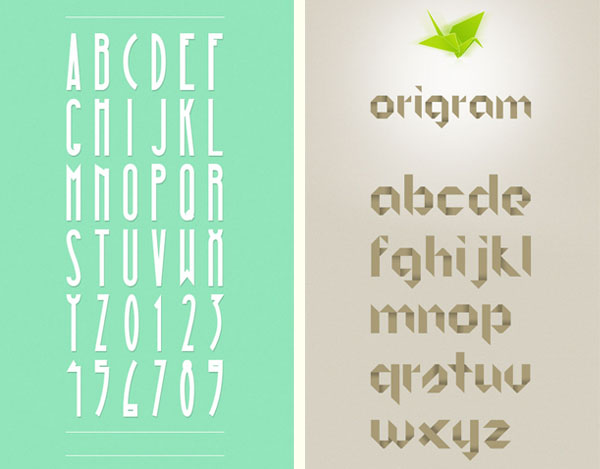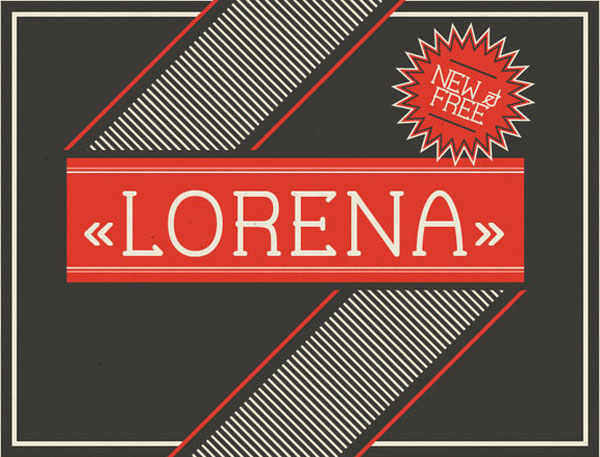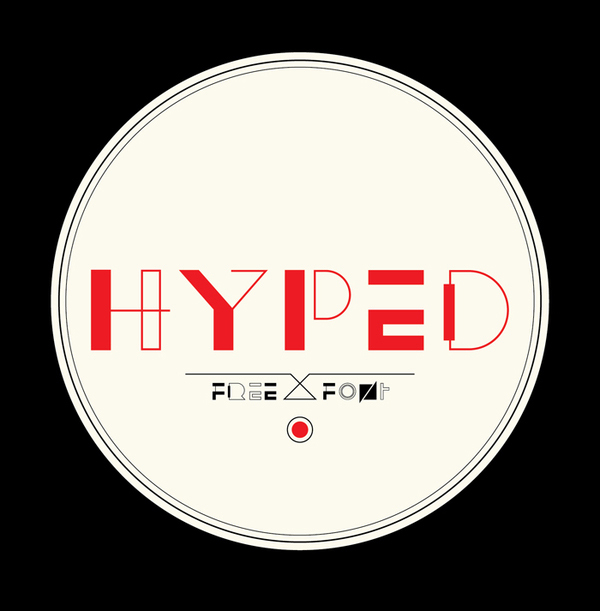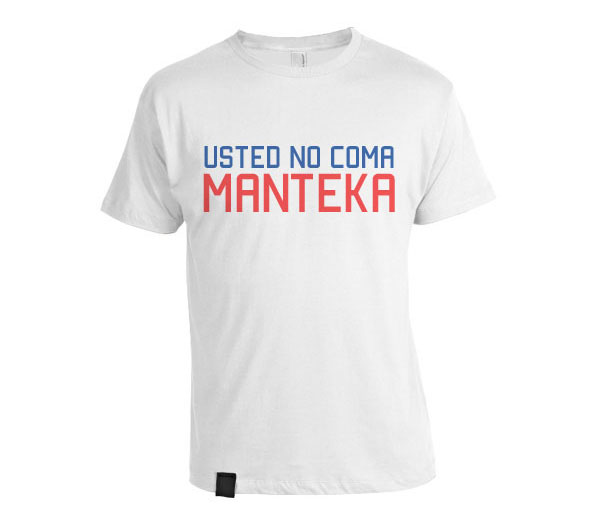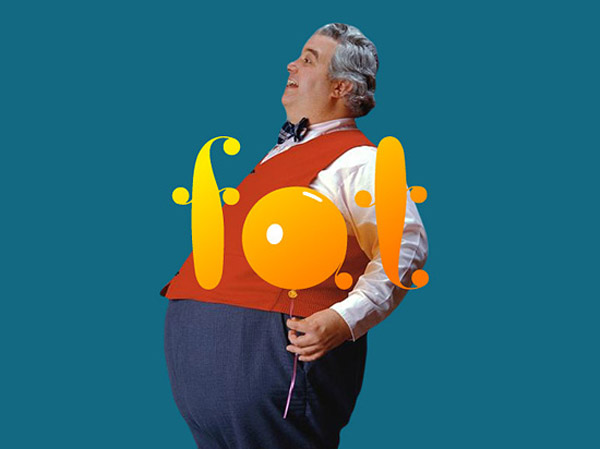
Webneel, la web dedicada a la difusisón de trabajos gráficos –ilustraciones, fotografías o animación entre otros– ha realizado una selección de 25 tipografías descagables de manera gratuita. Pensadas como una extraordinaria herramienta de trabajo para diseñadores, las tipografías son en múltiples ocasiones una verdadera obsesión. La selección realizada ofrece una gran variedad de estilos y diseños; a partir tanto de formas lineales como curvas, con una visión futurista o retro, esta selección tipográfica abarca desde las opciones más figurativas hasta las más sencillas pudiendo ser una gran aliada de los diseñadores.